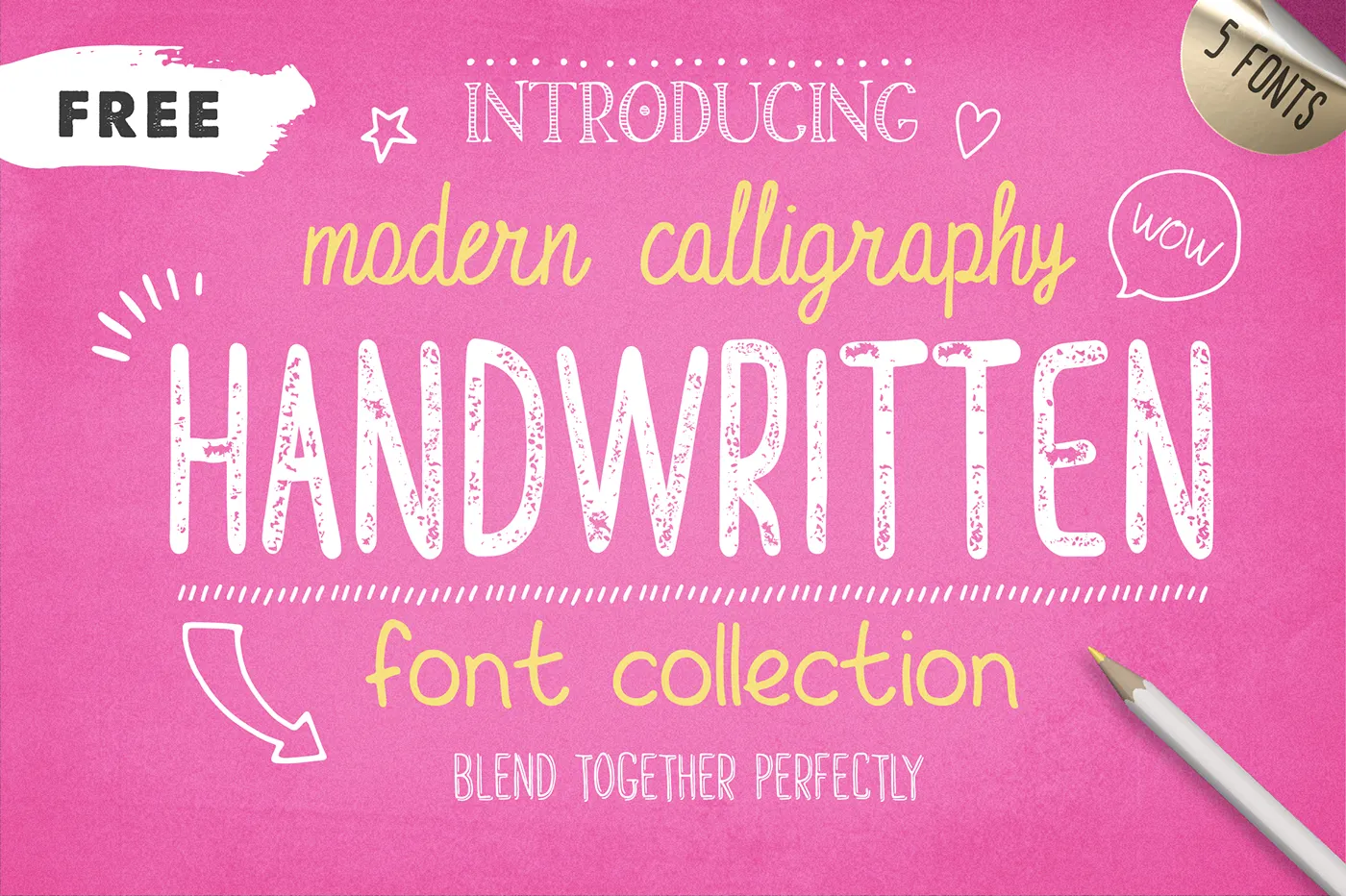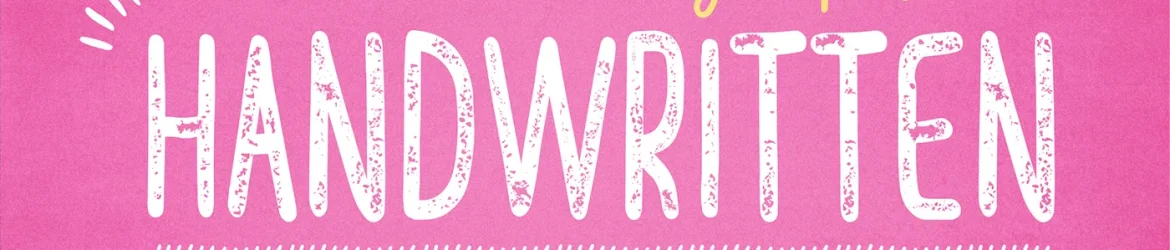
Handwritten Font Collection – Download Grátis
Introduzimos uma coleção de 5 fontes desenhadas à mão e 5 estilos alternativos criadas por Julia Dreams. Estas são projetadas para trabalhar perfeitamente com múltiplas aplicações, como convites de casamento, branding, logotipos, posts no Instagram, panfletos e muito mais. Estes fontes e elementos são ideais tanto para a criação da identidade corporativa de seu negócio ou logotipo para uma pequena loja. Também podem ser adicionados para decorar sua casa ou criar um convite de casamento. Adicione este belo conjunto de fontes e elementos para criar um cartão postal que representará o melhor do seu trabalho artístico. Agora, se você está a precisar rapidamente decolar no âmbito da criação visual e não sabe por onde começar, esta coleção de fóruns pode ser exatamente aquilo que precisa. Ela contém fontes únicas que vão fazer toda a diferença em seus projetos. Seja para o seu escritório ou para aquele projeto especial que você está trabalhando atualmente, estes são os atalhos perfeitos que vai precisar.